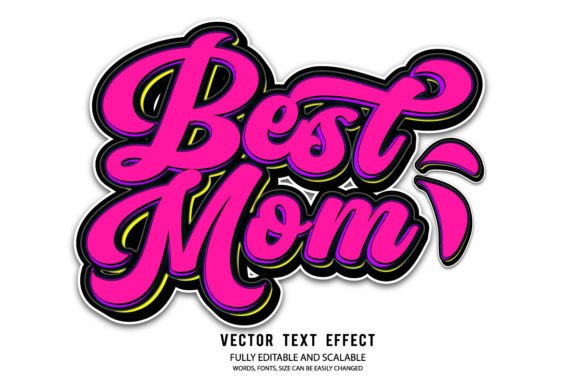
Editable Modern Lettering Typography
์˜ฌ๋ฐ”๋ฅธ ๋””์ž์ธ ์š”์†Œ๋ฅผ ์ฐพ๋Š” ๊ฒƒ์€ ์–ด๋ ค์šธ ์ˆ˜ ์žˆ์ง€๋งŒ Editable Modern Lettering Typography๋Š” ์ž‘์—…์„ ์ฆ‰์‹œ ํ–ฅ์ƒ์‹œํ‚ค๋Š” ๋›ฐ์–ด๋‚œ ์ปฌ๋ ‰์…˜์„ ์ œ๊ณตํ•ฉ๋‹ˆ๋‹ค.
POD(์ฃผ๋ฌธํ˜• ์ธ์‡„) ์ œํ’ˆ, ๊ฒฐํ˜ผ์‹ ์ดˆ๋Œ€์žฅ ๋˜๋Š” ์†Œ์…œ ๋ฏธ๋””์–ด ๊ทธ๋ž˜ํ”ฝ์„ ๋งŒ๋“ค ๋•Œ Editable Modern Lettering Typography๋Š” ์ด์ƒ์ ์ธ ์„ ํƒ์ž…๋‹ˆ๋‹ค.